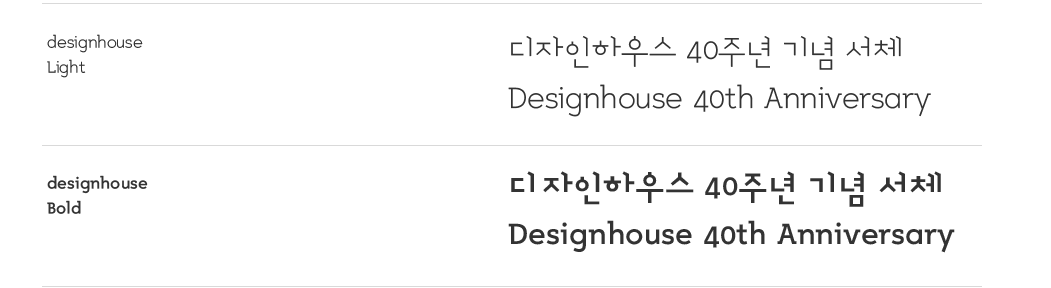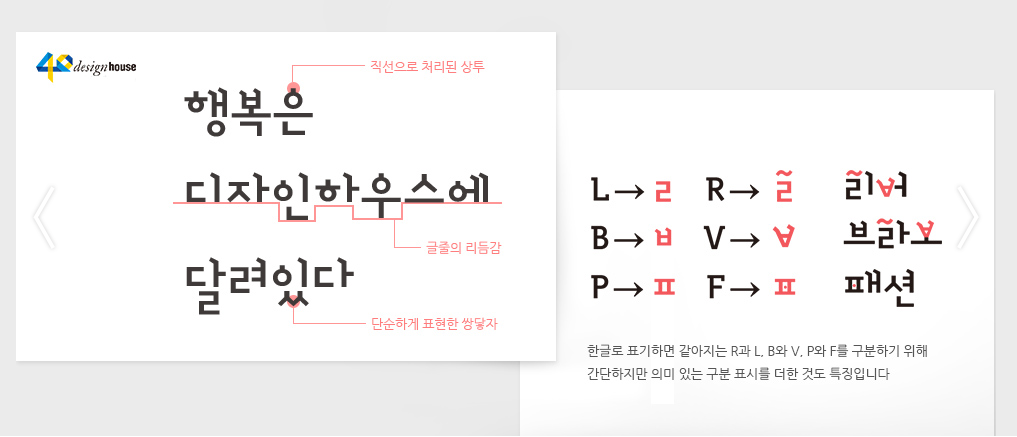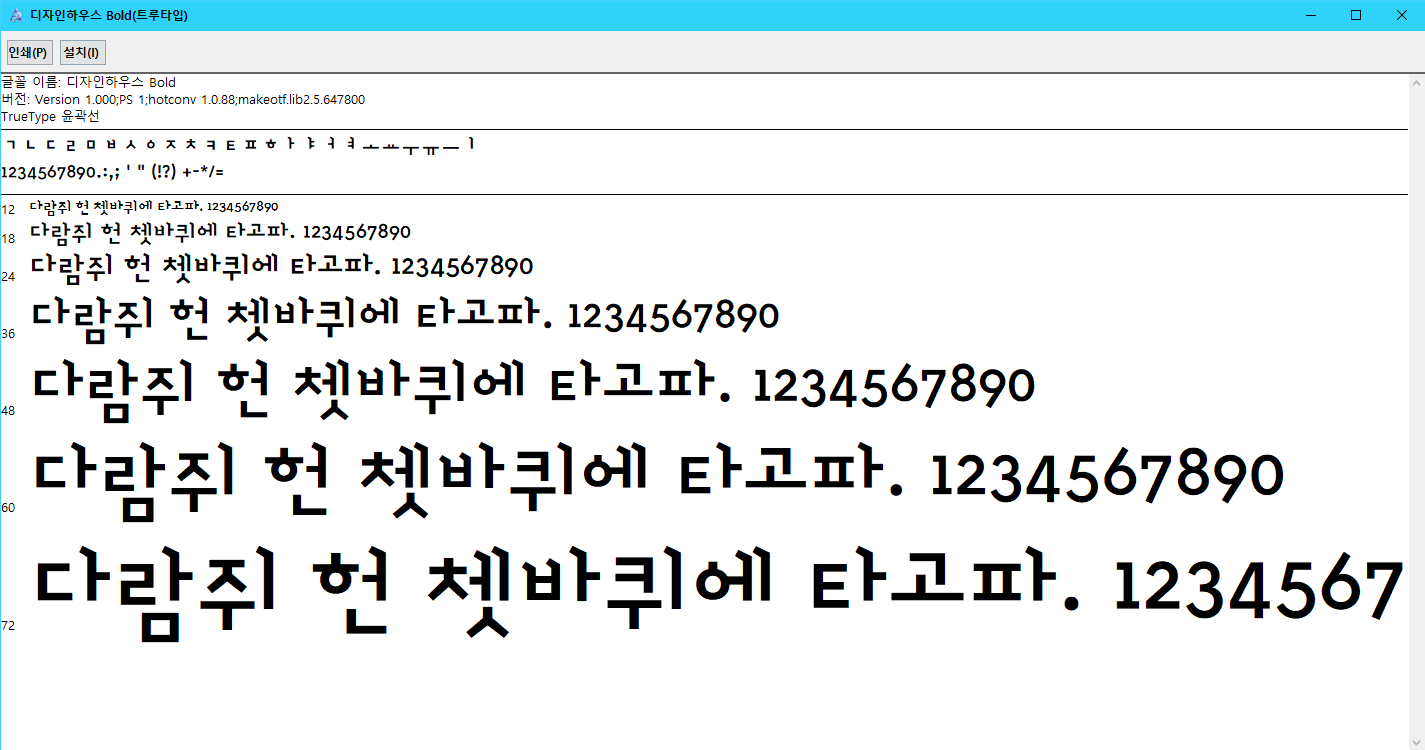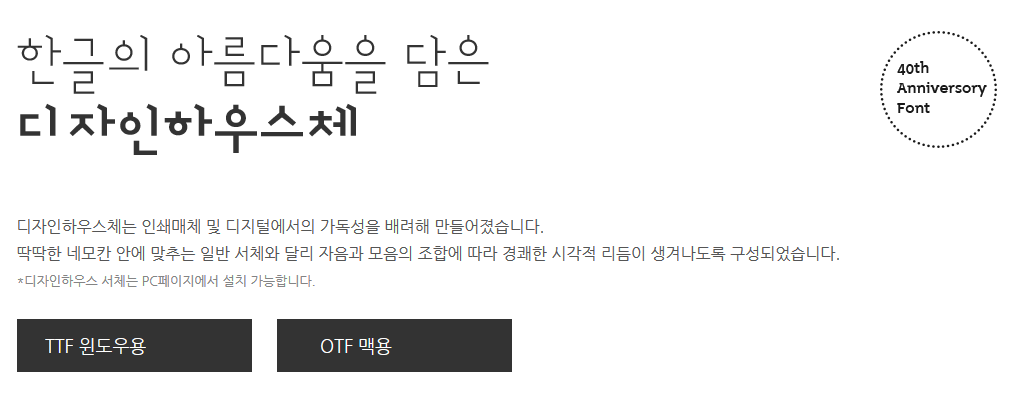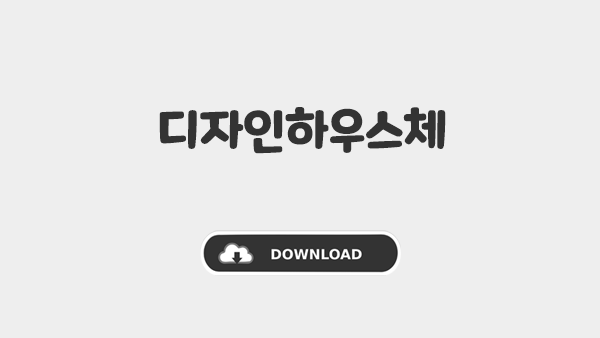
디자인하우스체는 인쇄매체 및 웹, 모바일 등의 디지털에서 가독성을 배려하여 제작된 폰트입니다. 딱딱한 네모칸 안에 맞추는 일반적인 한글 무료 폰트와는 달리 자음과 모음 조합에 따라 경쾌한 리듬이 생겨나도록 제작되었다고 하는데요.
디자인하우스체는 특이하게 외래어를 한글로 표기하는 방법이 일반적인 한글 폰트와는 다른 점이 있습니다. 알파벳 R과 L, V와 B, F와 P를 구분하기 위하 표기하는 방식이 다르다는 점이 정말 특이한 매력이 있는 한글 폰트인 것 같습니다.